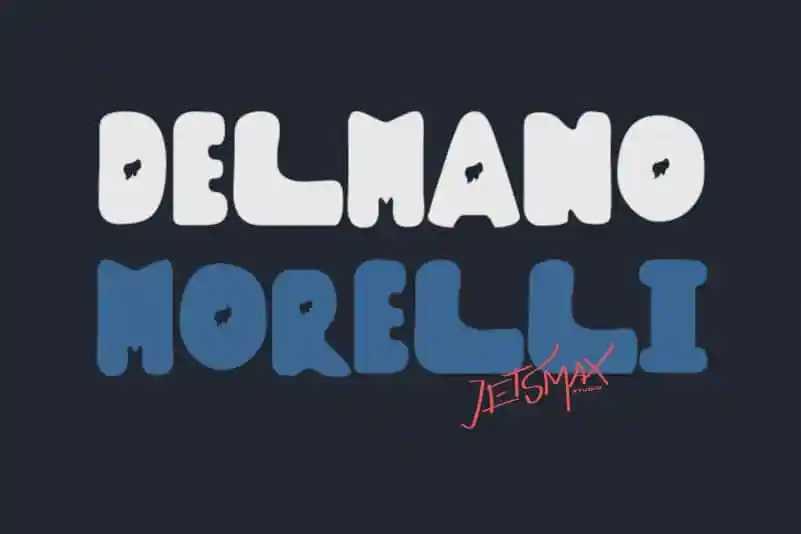
Delmano Morelli Display Font – Download Grátis
Delmano Morelli Display Font é uma elegante escolha para projetos que exigem destaque e sofisticação, inspirada nos enfeites tipográficos vintage dos filmes dos anos 1920, quando as produções cinematográficas começaram a explodir na indústria. Sua riqueza de detalhes e linhas robustas garantem um acabamento requintado em qualquer projeto visual que ela seja empregada. O designer jetsmax criou esta font para ajudar você a capturar o espírito dos tempos, tornando qualquer design project exuberante e imponente, sem perder a elegância necessária. A Delmano Morelli Display Font é uma ótima opção para quem quer dar vida nova ao seu projeto gráfico, com um toque de nostalgia que remete aos anos 1920.